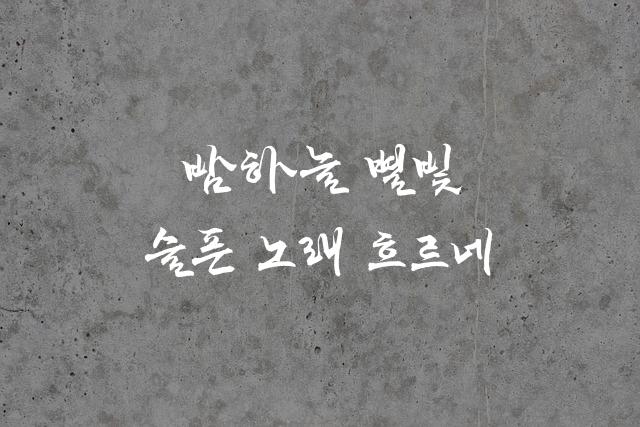
밀양해맑은상상체는 붓글씨와 캘리그라피에서 영감을 받은 한국어 폰트입니다. 이 폰트는 감성적이고 창의적인 표현을 가능하게 해줍니다.
밀양해맑은상상체은(는)
손글씨, 펜/붓터치, 감성적인 계열의 생김새를 가지고 있으며
어린이 책, 인사말 카드, 일기/편지 등에서 자주 활용되며, 효과적인 메시지 전달에 적합합니다.
이 폰트는 음식/식음료, 라이프스타일, 유아/가족 분야에 잘 어울리며,
따뜻한, 친근한, 편안한 느낌을 담고 있는 것이 특징입니다.